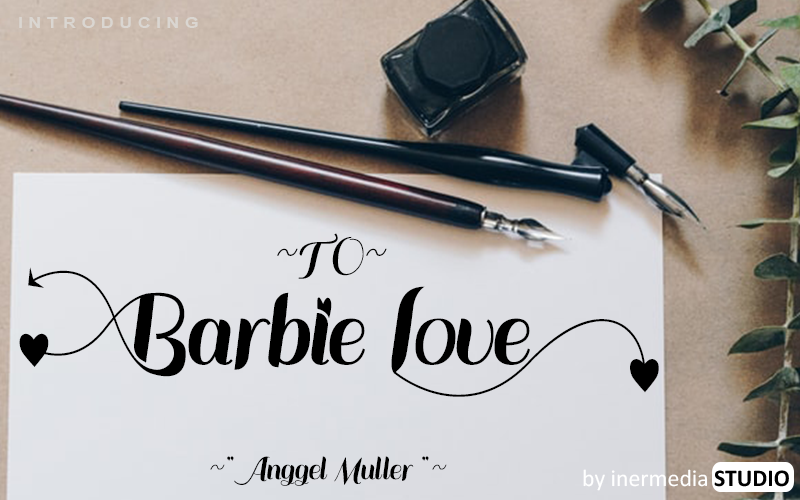
A Barbie Love Font é uma escolha perfeita para designers que valorizam a elegância dos estilos escriturísticos enquanto não abrem mão do frescor contemporâneo. Seu design conserva os elementos refinados que tornam o estilo calligráfico tão apreciado, mas adicionando uma leve modernidade e atualização ao mesmo tempo. Esta fonte é versátil e pronta para diferentes propósitos, seja criando cartões de apresentação com um tom sofisticado ou produzindo materiais de escritório e estilizados para festivais e eventos. É perfeita para qualquer projeto que exija um acabamento elegante e atemporal.